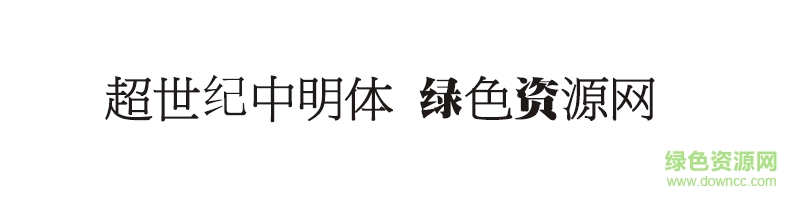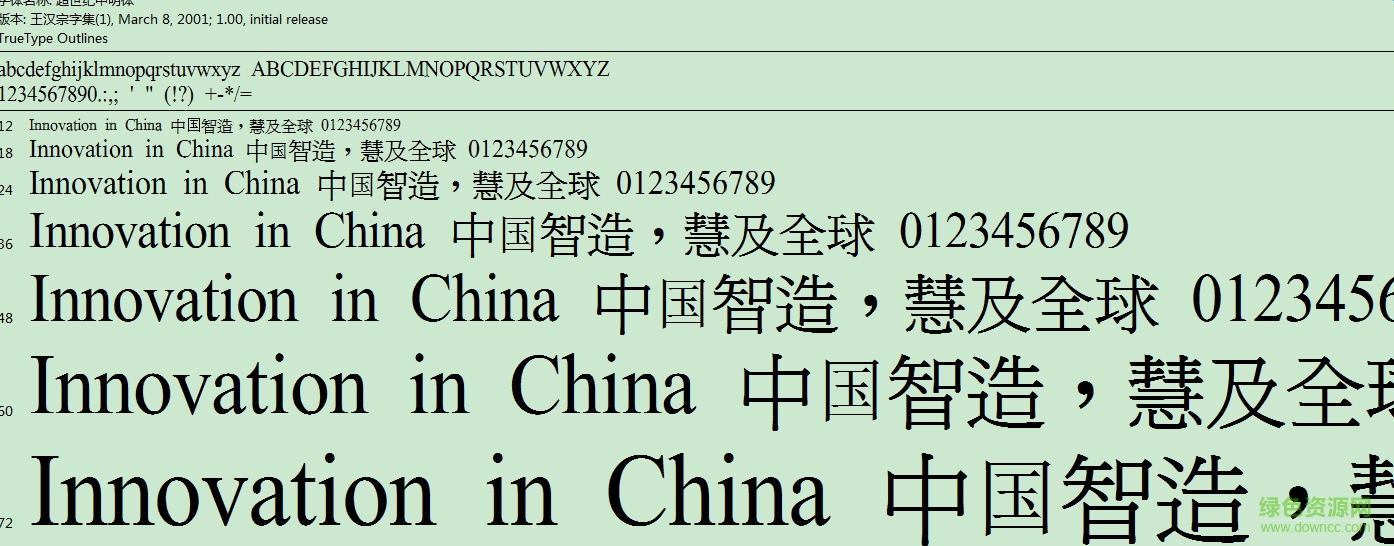
超世紀(jì)中明體是一款在超世紀(jì)字體中比較好玩的字體格式,很多朋友都在尋找,小編為大家?guī)?lái)免費(fèi)下載地址,修長(zhǎng)美觀,做藝術(shù)字體的朋友不要錯(cuò)過(guò)。歡迎大家來(lái)綠色資源網(wǎng)踴躍下載哦!
超世紀(jì)中明體字體以中明體字形結(jié)構(gòu)為特點(diǎn),其字融合書(shū)法技法,運(yùn)筆意趣剛?cè)嶙厩?、緊中見(jiàn)放、氣韻生動(dòng)。風(fēng)格娟秀潤(rùn)雅,筆力勁挺又不失端正,能夠適用于產(chǎn)品包裝、廣告宣傳、海報(bào)設(shè)計(jì)、網(wǎng)頁(yè)廣告設(shè)計(jì)等應(yīng)用。